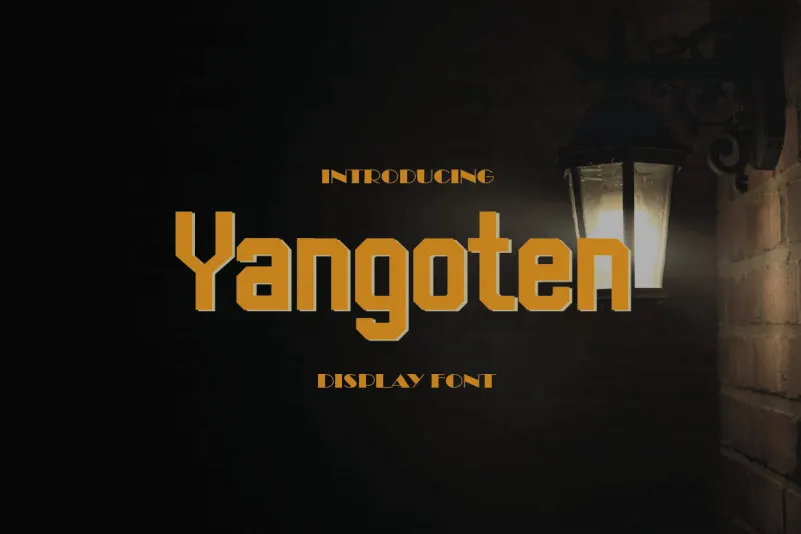
Yangoten Font – Fonte Grátis
Yangoten Font
A Design Amour apresenta a Yangoten Font, uma elegante fuente display que parece direto de um display digital moderno. Especificamente criada para destacar suas criações digitais e posters, esta fonte oferece um design único e vibrante. Seu aspecto de tela digital combinado com sua versatilidade em aplicação a postagens dá uma aparência chamativa e moderna a qualquer projeto de desenho. Ideal para designers que procuram uma fuente chamativa que brilha em ambientes digitais, Yangoten oferece um toque único à experiência visual do design.